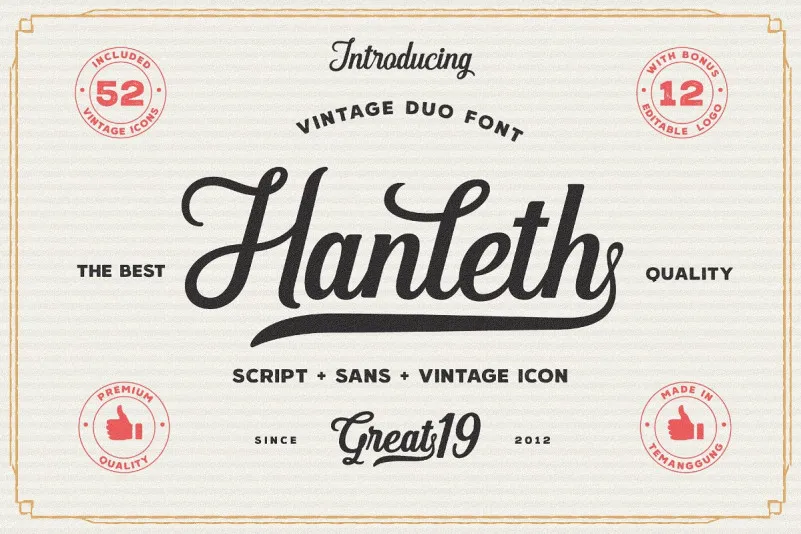
Hanleth Vintage Font Duo – Fonte Grátis
Hanleth Vintage Font Duo
Esta font foi inspirada nos rótulos antigos de denim vintage, no velho oeste, mas é uma criação única e memorável. Ideal para uso em logotipos, anúncios, convites, roupas e muito mais. Introduzimos Hanleth Font, que foi desenhado e compartilhado por great19. Com seu design elegante e forte, a font Hanleth Vintage Font Duo é uma opção perfeita para quem busca criar mensagens memoráveis em diversas aplicações digitais. Com seus traços sóbrios e detalhes distintos, a fonte combina com diferentes estilos de design, desde os mais simples até aqueles que exigem um toque sofisticado. Ideal tanto para criação personalizada como para trabalho profissional, Hanleth Vintage Font Duo é uma escolha inteligente para designers de gráficos e criativos do mundo todo.